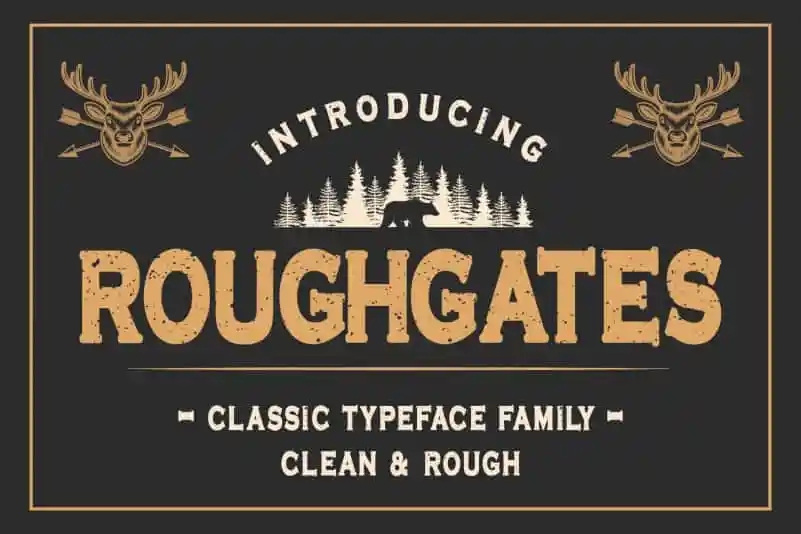
Roughgates Display Font – Fonte Grátis
Roughgates Display Font
Roughgates Display Font é uma tipografia de exibição que apresenta uma letra assertiva e rústica. Ideal para estilos vintage, esta sans serif proporciona um visual nostálgico moderno. Com suporte a múltiplas línguas incluindo caracteres ocidentais, essa fonte traz um toque de personalidade aos projetos digitais sem comprometer o uso em diversas situações. Perfeito para criar efeitos vintage em designs de sites, aplicativos ou banners, Roughgates Display Font é uma escolha ideal para quem busca dar um toque retro a seu material sem sair da linha moderna. Suportando várias línguas e caracteres ocidentais, a fonte Mozarella oferece flexibilidade para adaptar seu estilo a qualquer projeto que precise de um tom vintage e contemporâneo.